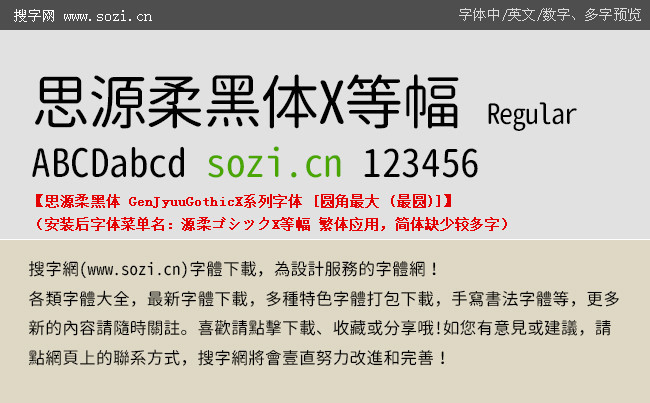
思源柔黑体X等幅-Regular
搜字网给大家提供一款思源柔黑体X等幅-Regular中文字体下载,思源柔黑体由思源黑体改造而来,由日本作者自家製フォント工房制作,所以部分简体中文可能会不显示,字柔黑承袭了「思源黑体」原有的优雅,在文字边角以圆边进行处理,相比原来思源黑体更加柔和,似黑似圆,介于二者之间,而X系列圆角最大 (最圆)。适用于大标题、包装设计、海报设计等应用。